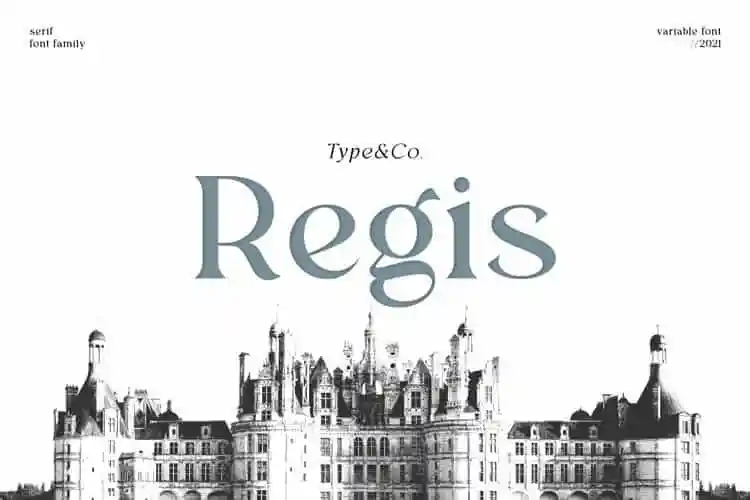
A Regis Serif Font é uma elegante tipografia serif que traz a conveniente combinação de linhas modernas e harmonia entre as letras. Criada pela type & co., essa fonte não só oferece um aspecto refinado para textos, mas também incorpora alternativas e ligaturas que adicionam profundidade e interatividade aos seus projetos. Com uma estrutura de serif clara e armoniosa, o Regis é perfeito tanto para criações tradicionais quanto para ideias modernas. Suportando múltiplos idiomas, ele traz um toque sofisticado às suas obras, proporcionando um visual atraente. Esta fonte serifa clean está altamente adaptável para uso em livros e magazines, capas de revistas, editoriais, headlines, websites, logotipos, convites e marcas de marca, bem como anúncios e outros materiais gráficos. Adicione-a aos seus projetos mais criativos e observe como ela os destaca!